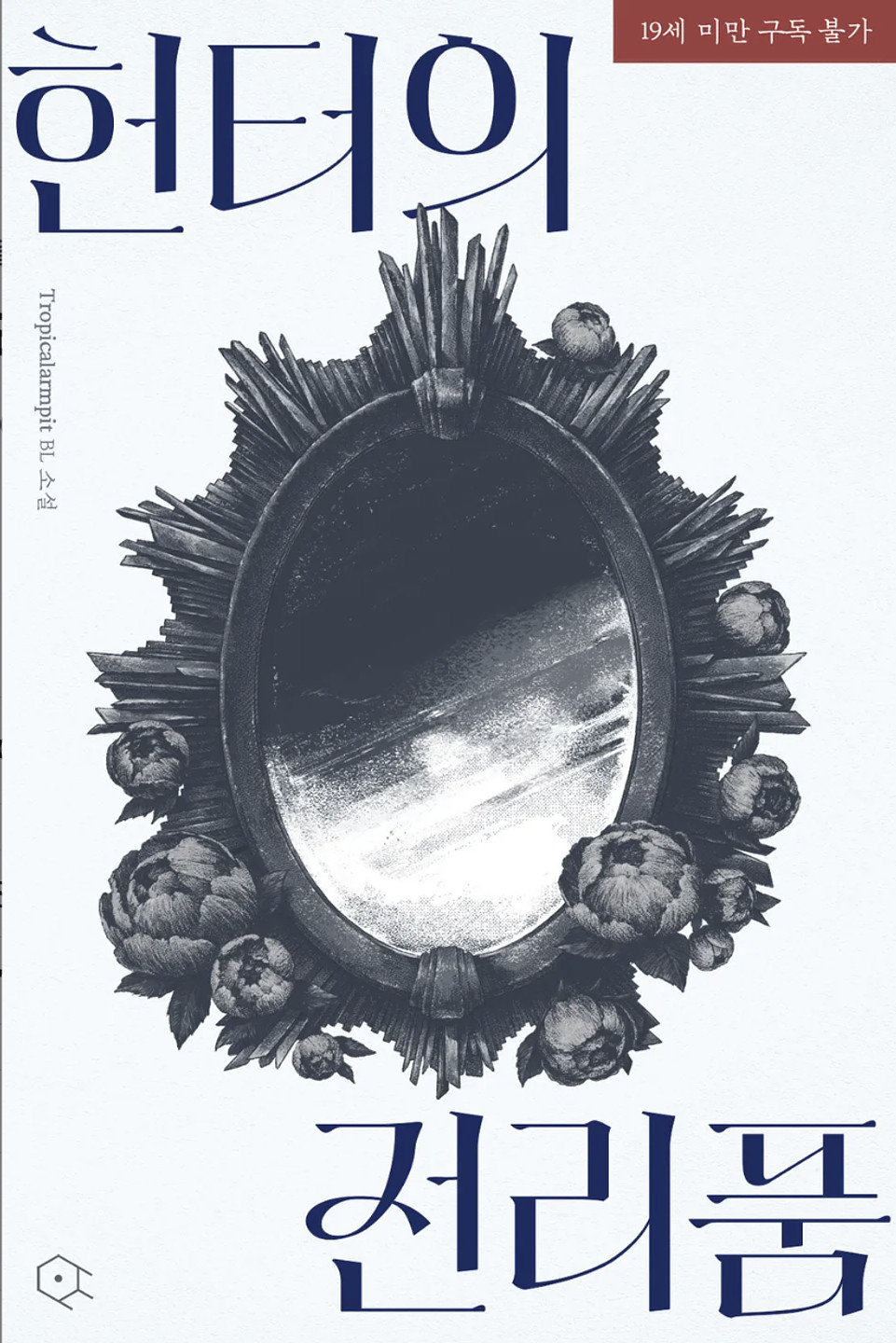
'헌터의 전리품' 여기 쓴 폰트 혹시 어떤 폰트인지 아시는 분 계신가요? 비밀정원이랑은 ㄹ이랑 ㅍ, ㅎ 획이 달라서 다른 폰트인 거 같습니다 ㅠㅠ
HS봄바람체 4.0
HS봄바람체 4.0입니다. https://smartstore.naver.com/typofoundry/products/10197995354